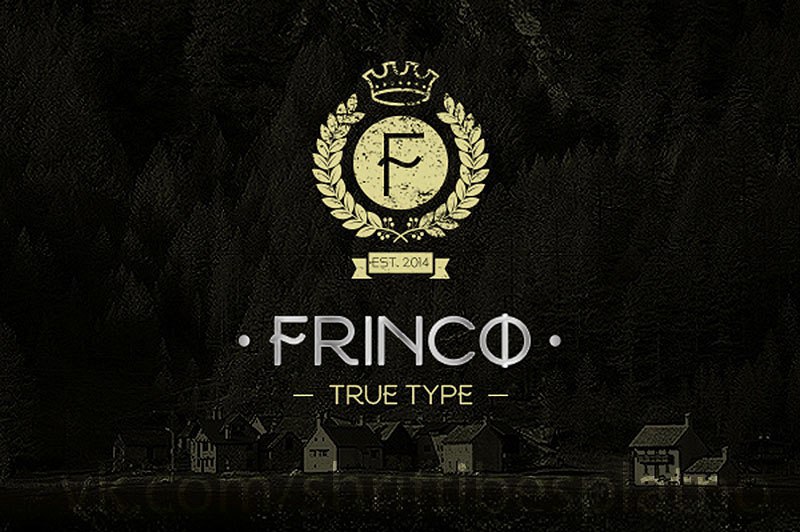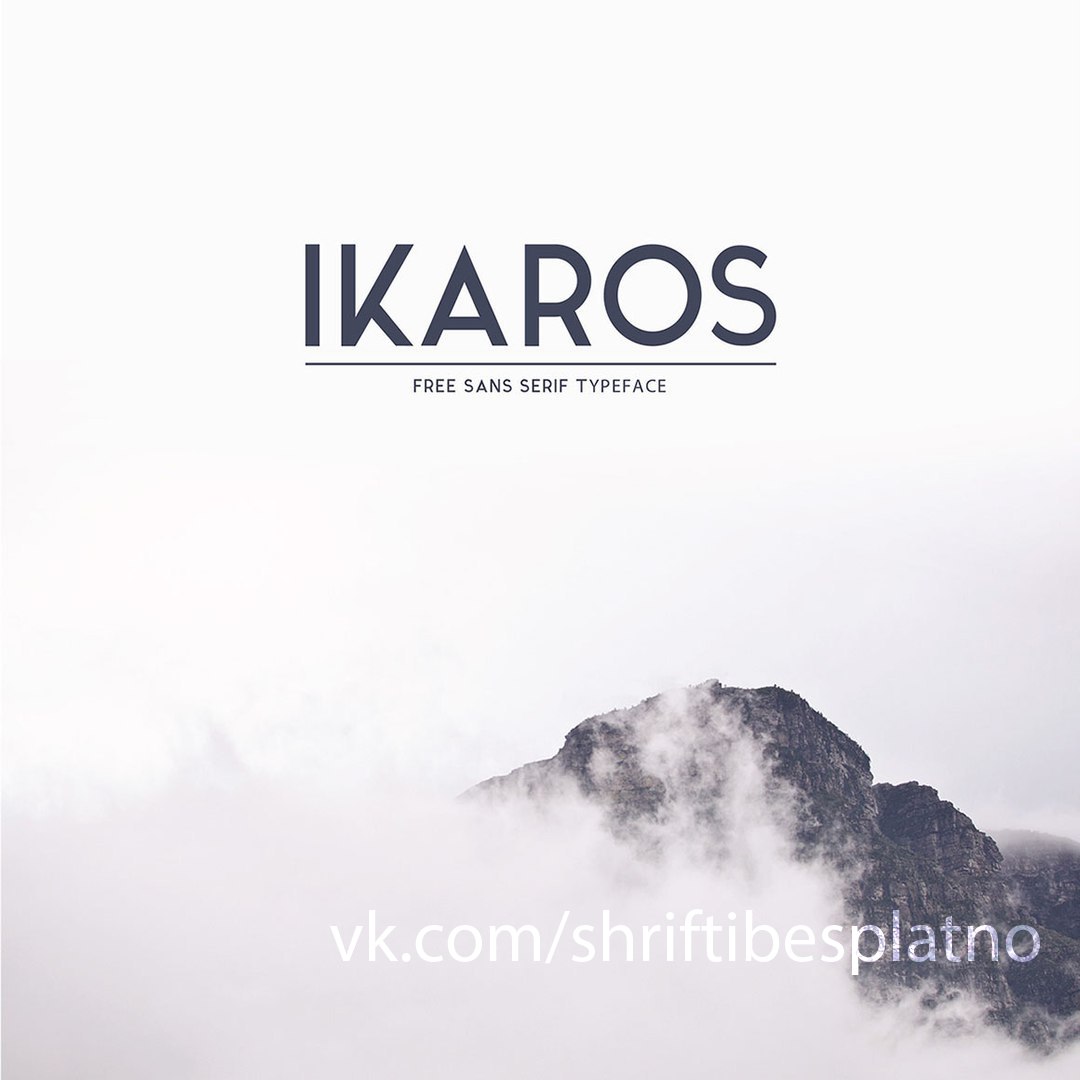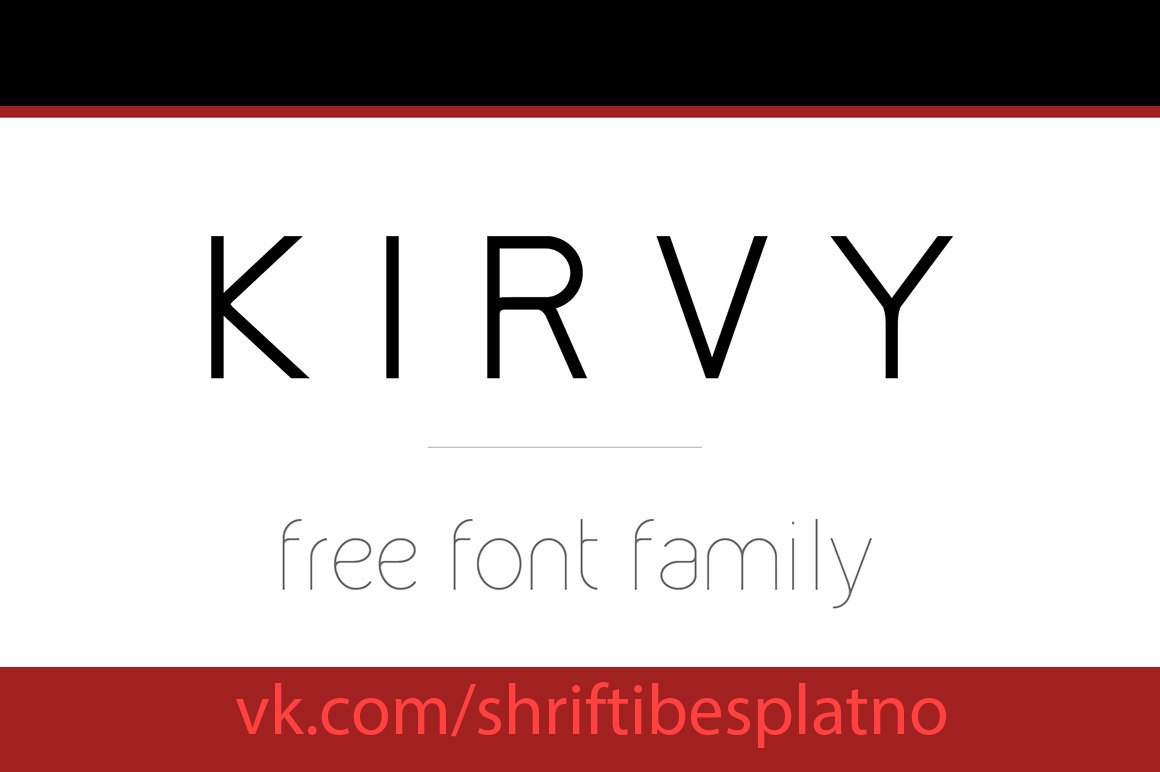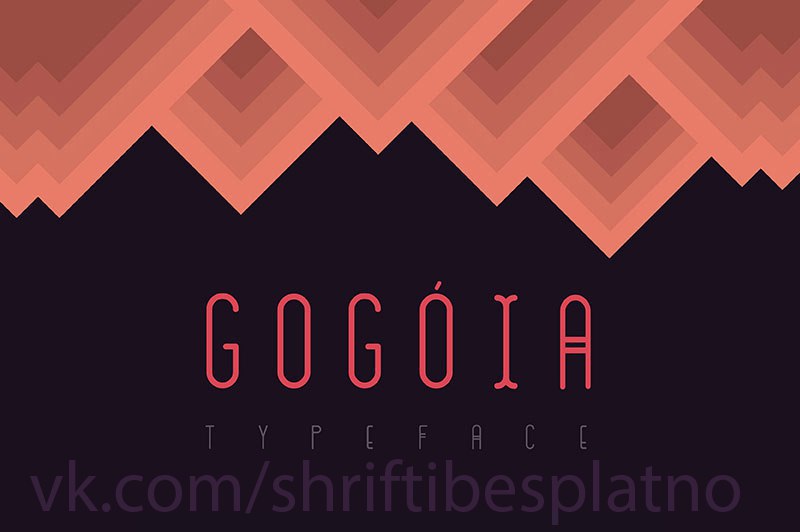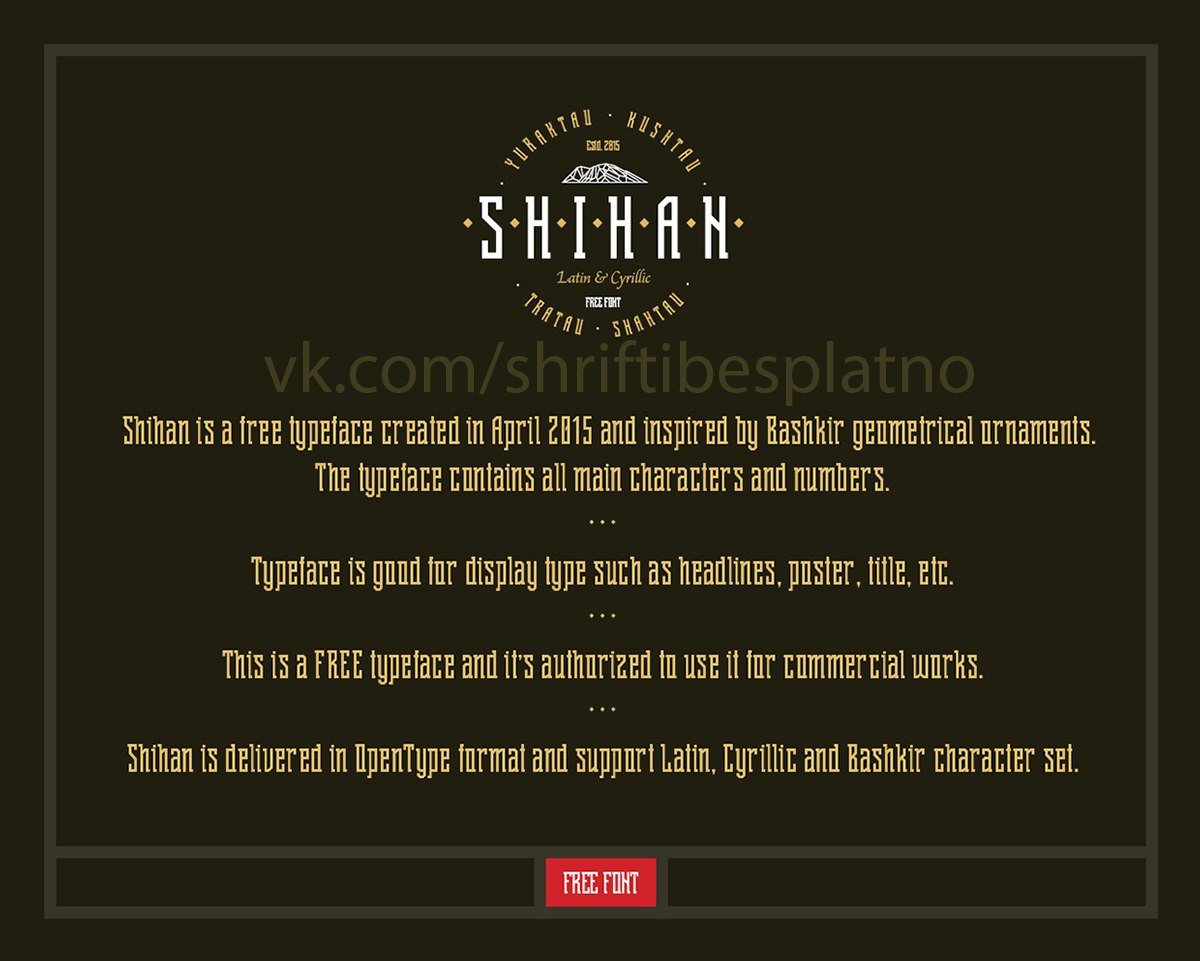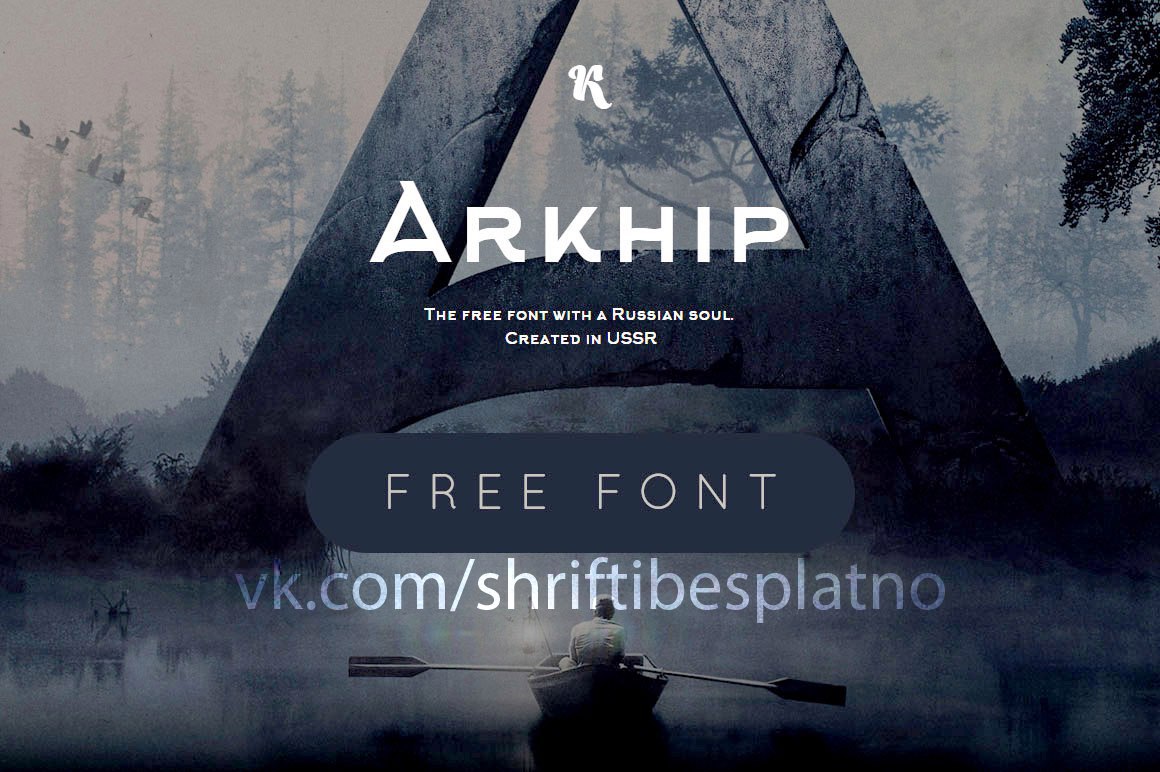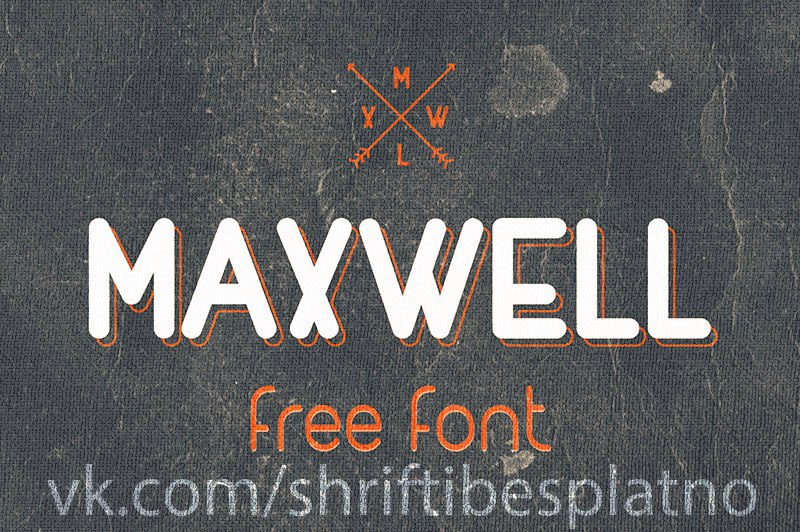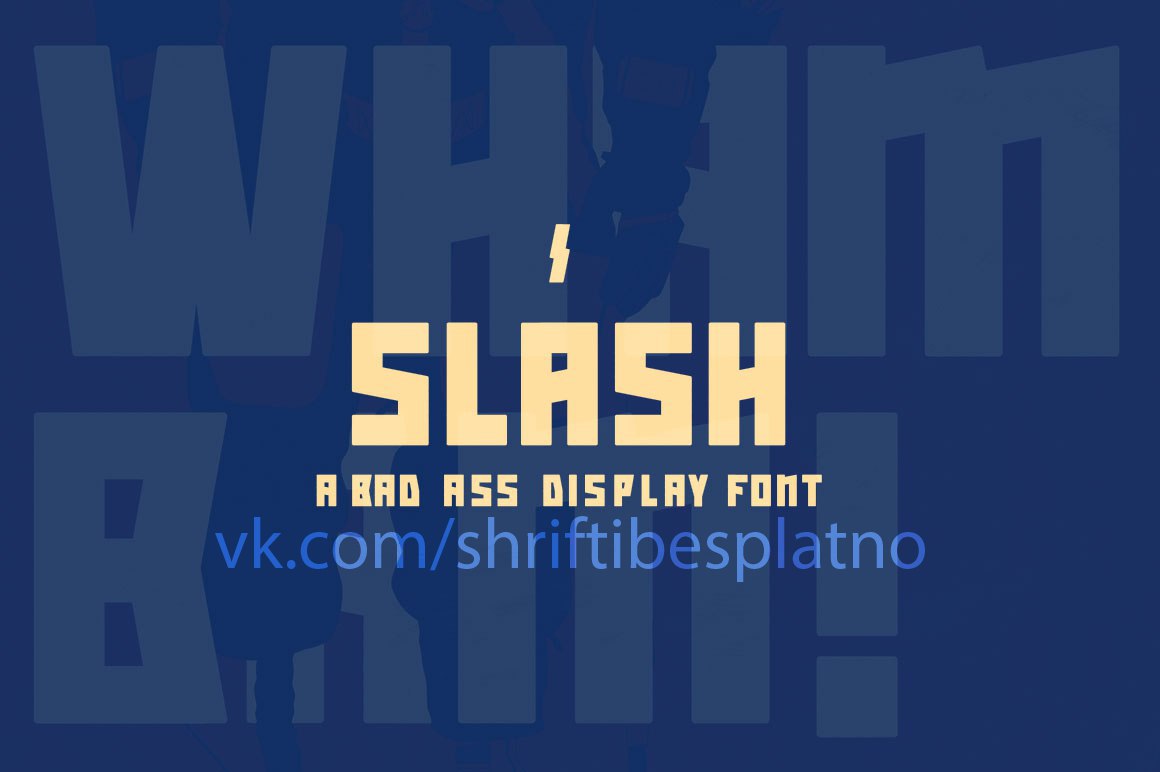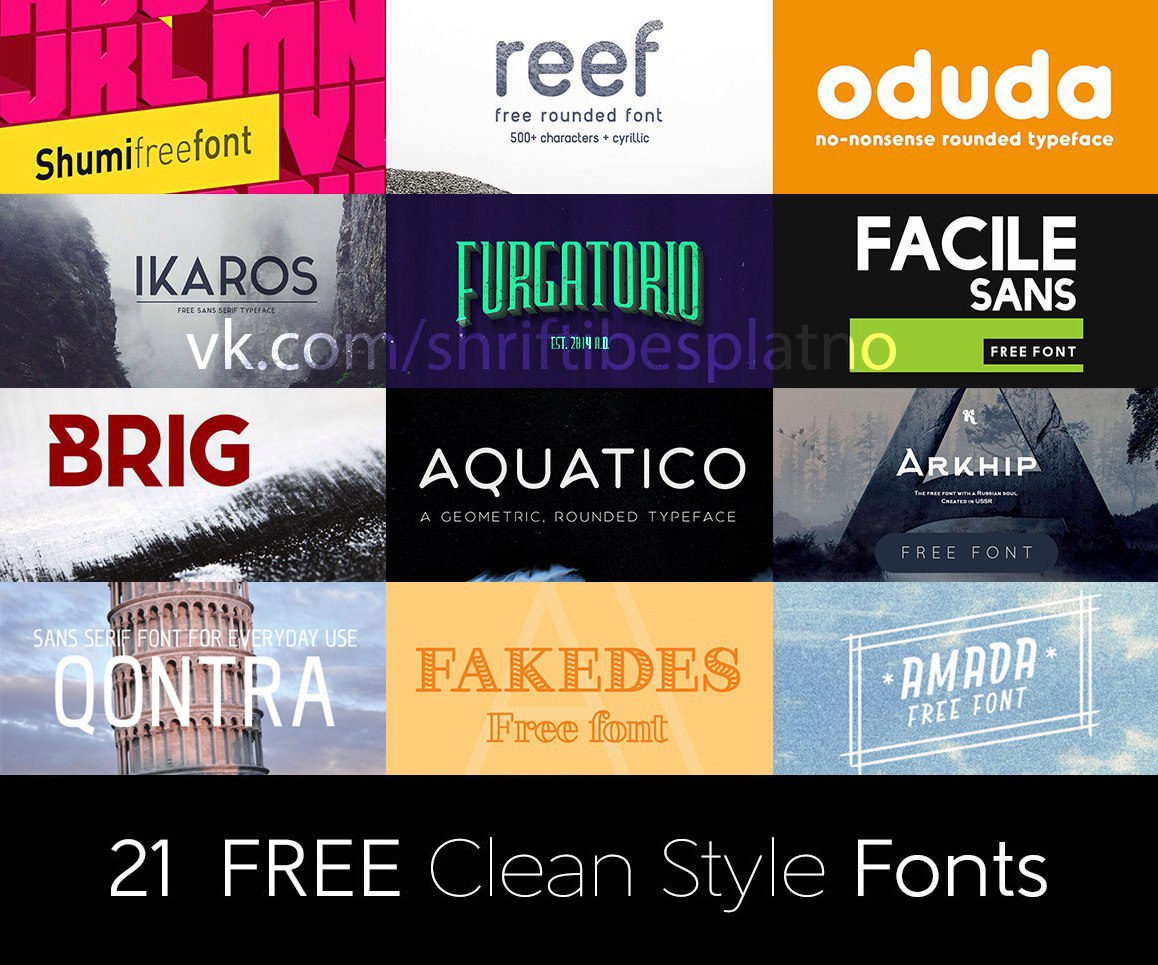
21 шрифт для наших участников:
В этом паке не только кириллица.
1. Aquatico – Бесплатный гротеск by Andrew Herndon
2. Brig – Бесплатный шрифт by Filipe Rolim
3. Qontra – Бесплатный шрифт без засечек Font by Tomaz Hrastar
4. Oduda – Бесплатный шрифт by Thom Niessink
5. SYNTHESIA – Free Font by Cahya Sofyan
6. Shumi – Free Font by Ivan Shumikhin (кириллица)
7. Marske – Бесплатный шрифт by Kash Singh & Sergiy Tkachenko (кириллица)
8. Amada – Free Font by Edu Oliveira
9. MadSquire – Бесплатный шрифт by Nele Tullus
10. Furgatorio – Free Font by Aaron Amar
11. Ikaros – Free Sans Serif Font by Matt Ellis
12. Reef – Free Rounded Font by RIT Creative (кириллица)
13. Shihan – Бесплатный шрифт by Sergey Godovalov (кириллица)
14. Fakedes – Free Serif Font by Cyril Mikhailov (кириллица)
15. Slash – Free Display Font by Ronald Vermeijs
16. GOGÓIA – Free Font by Alan de Sousa
17. Kirvy – Free Font Family by Youssef Habchi
18. Facile Sans – Free Clean Font by Twicolabs
19. Arkhip – Free Font with Russian Soul by Design Klimov (кириллица)
20. Frinco – Free Creative Font by Ryan Pyae
21. MAXWELL – Free Retro Font by Ryan Pyae